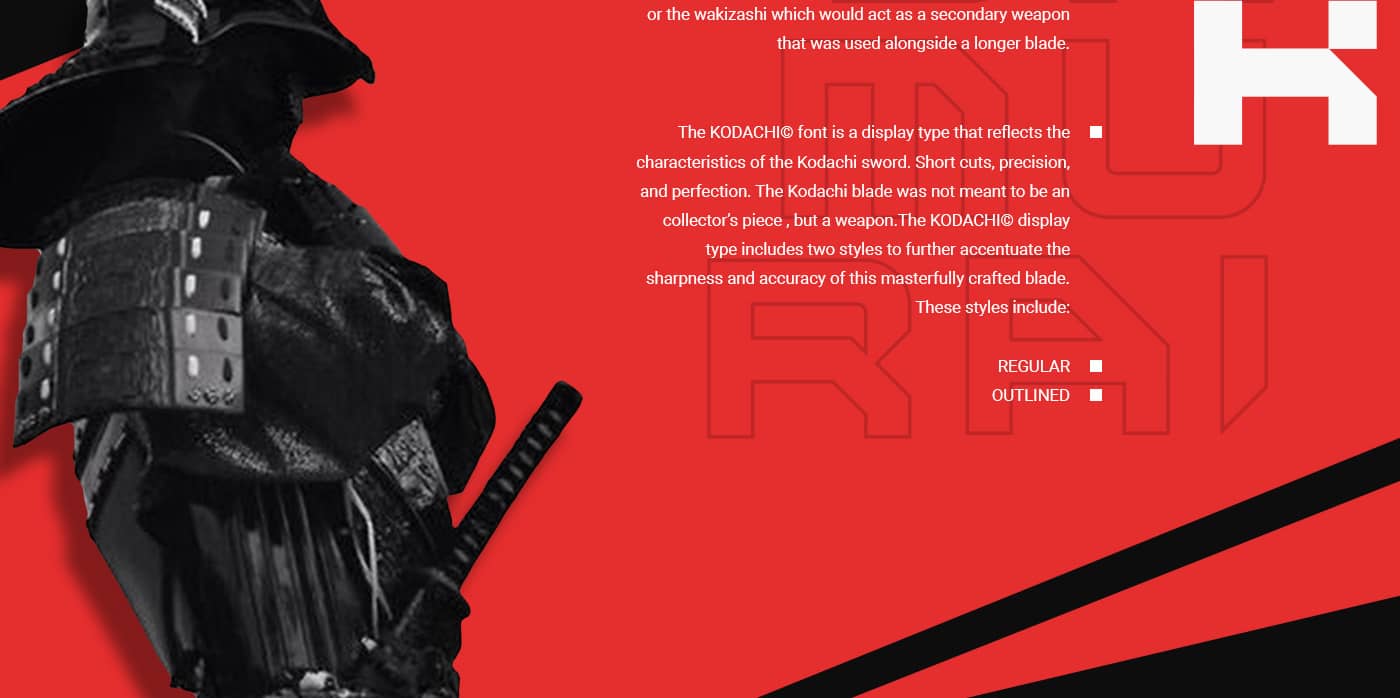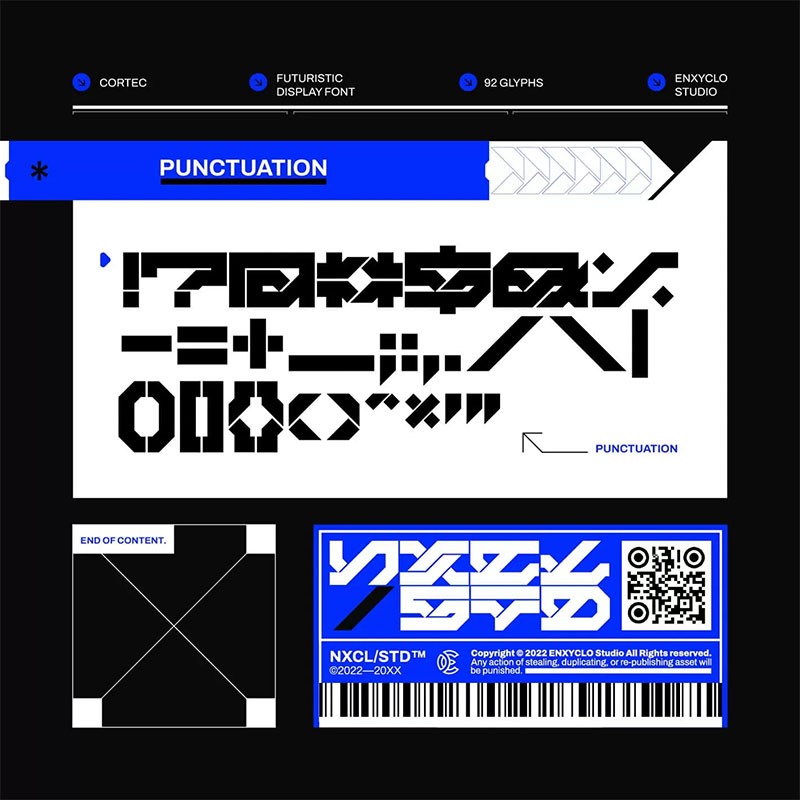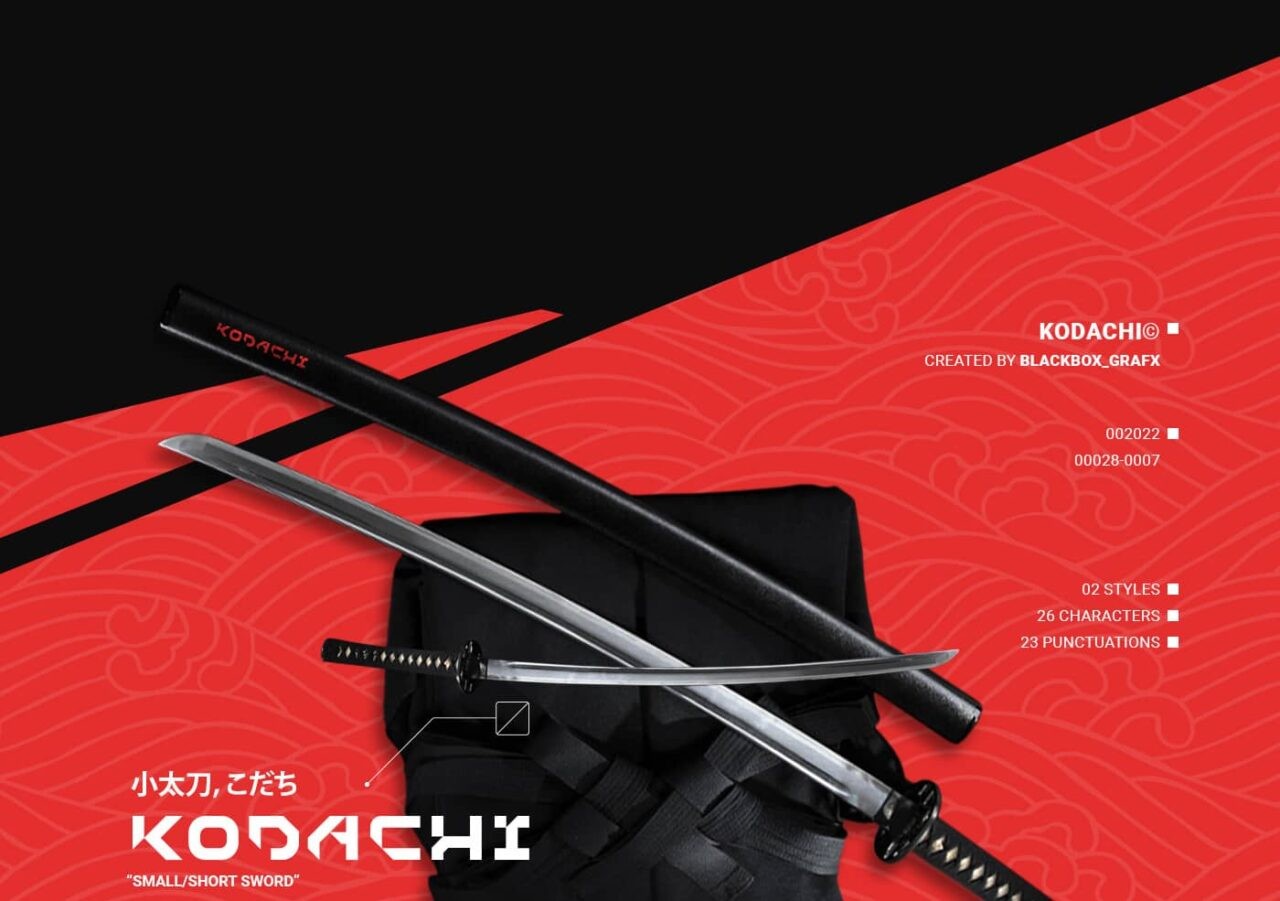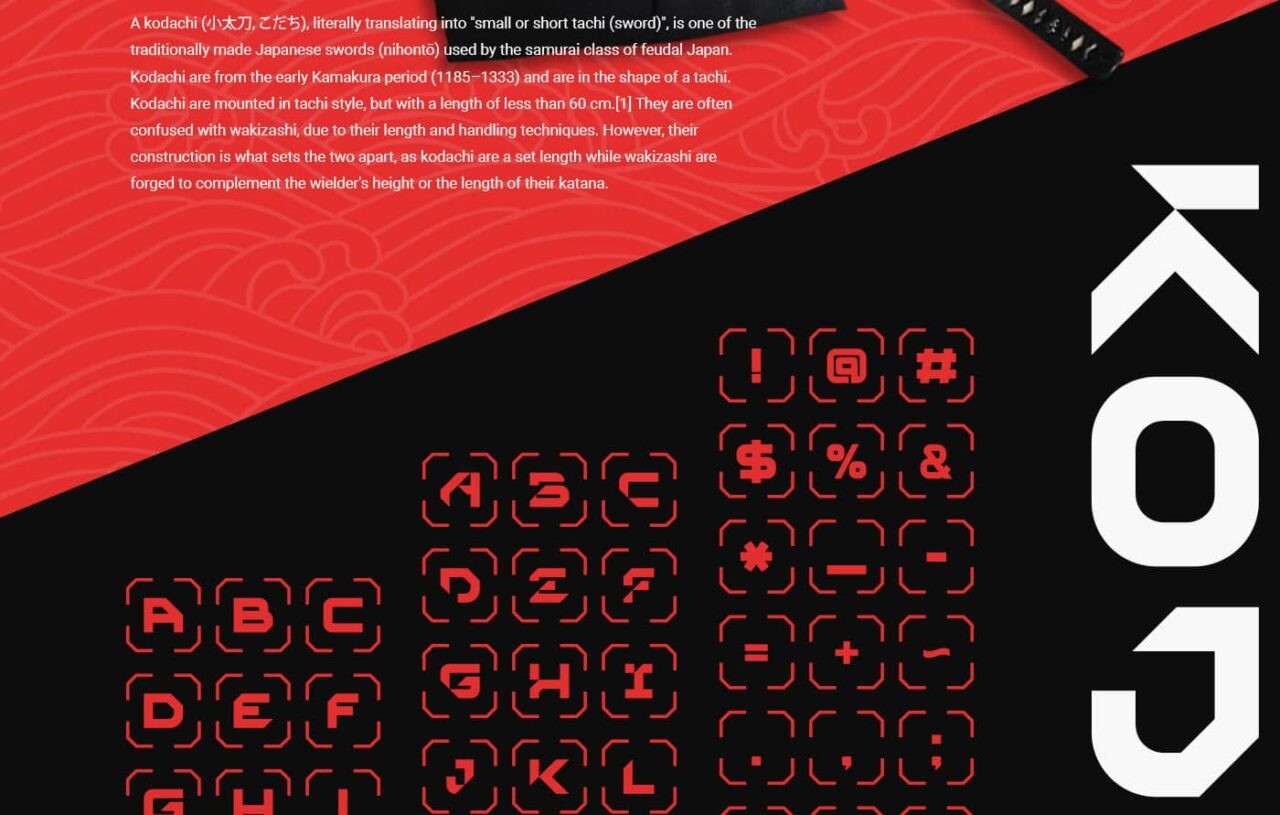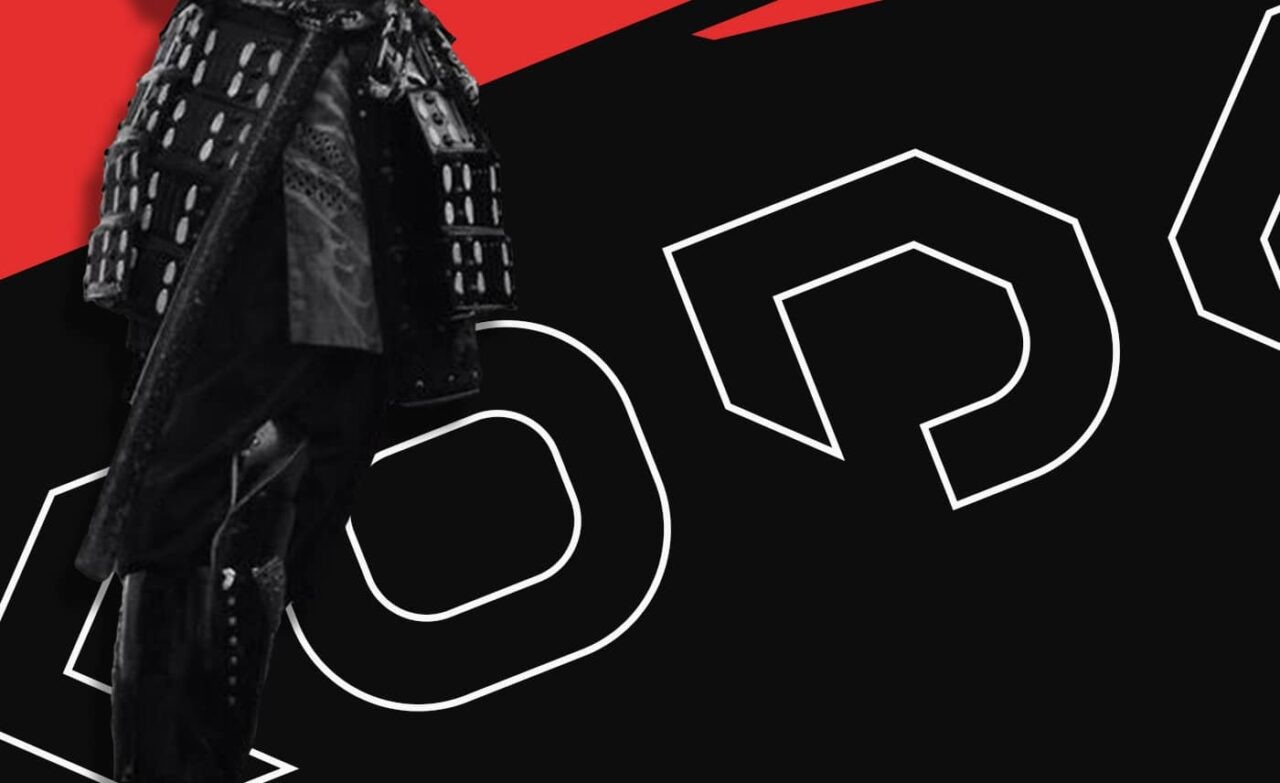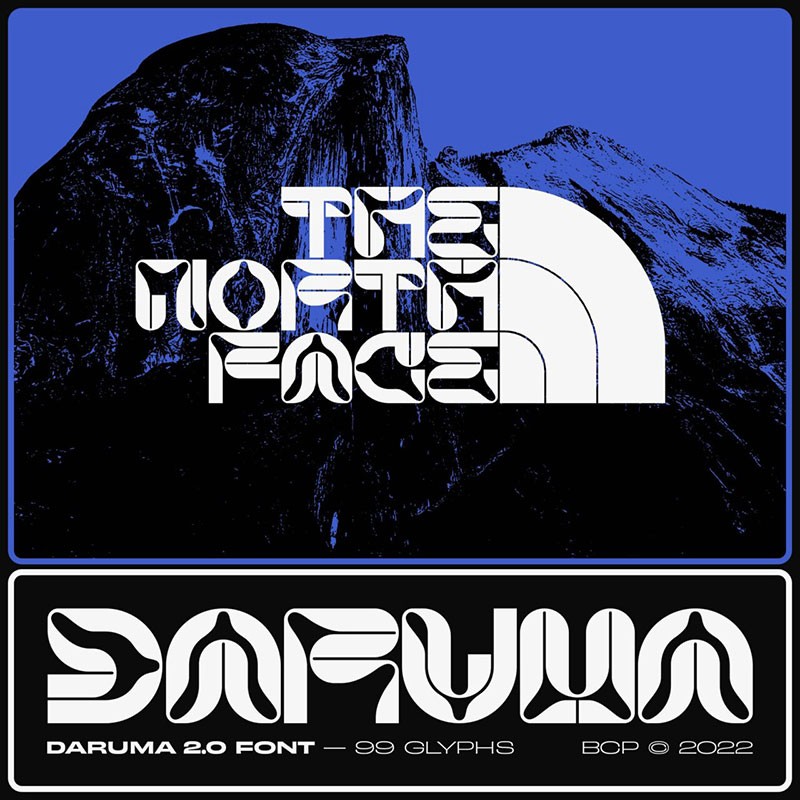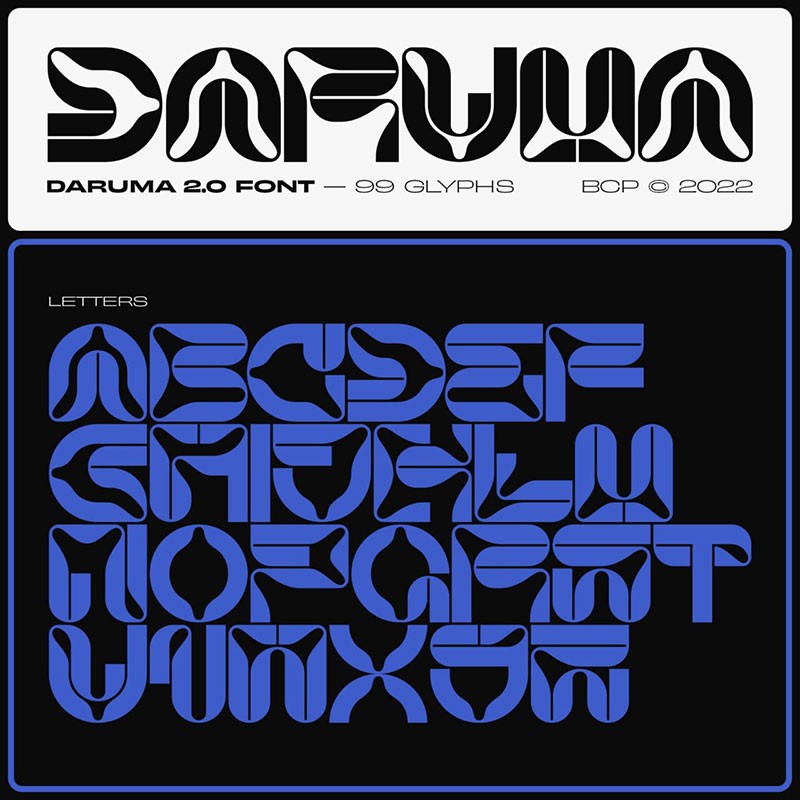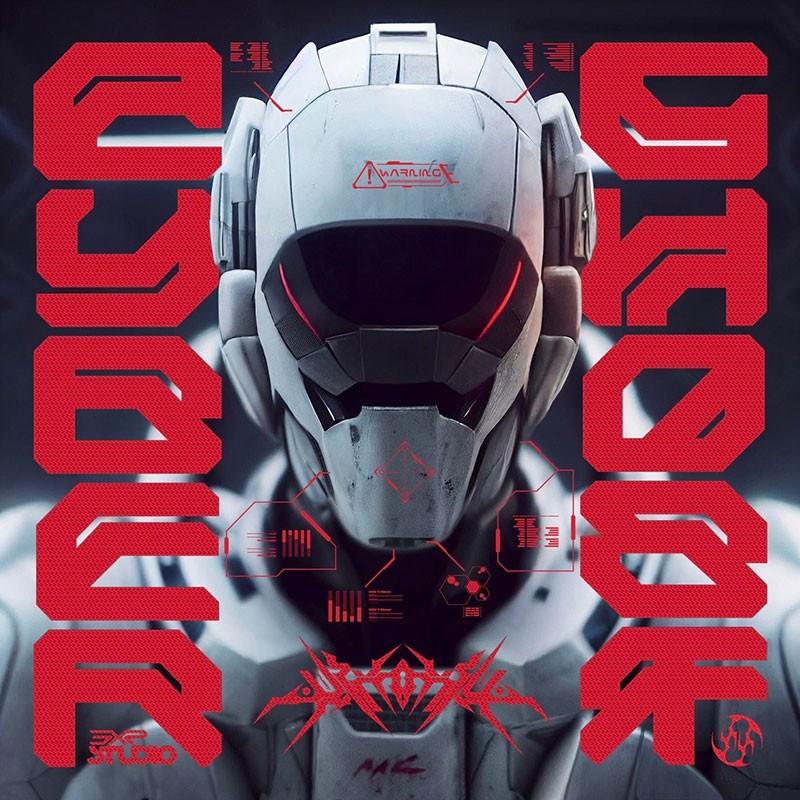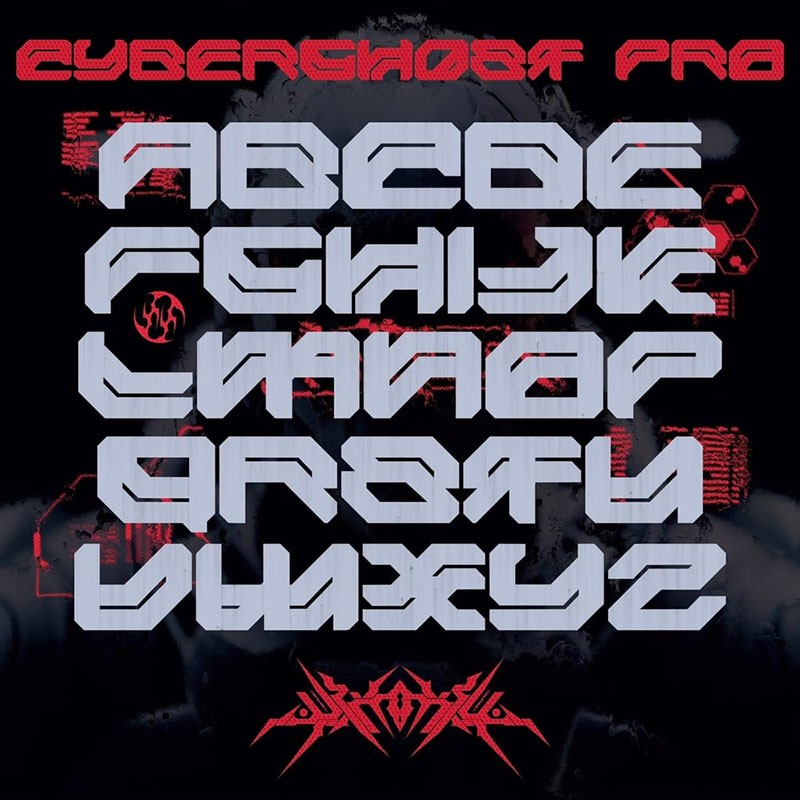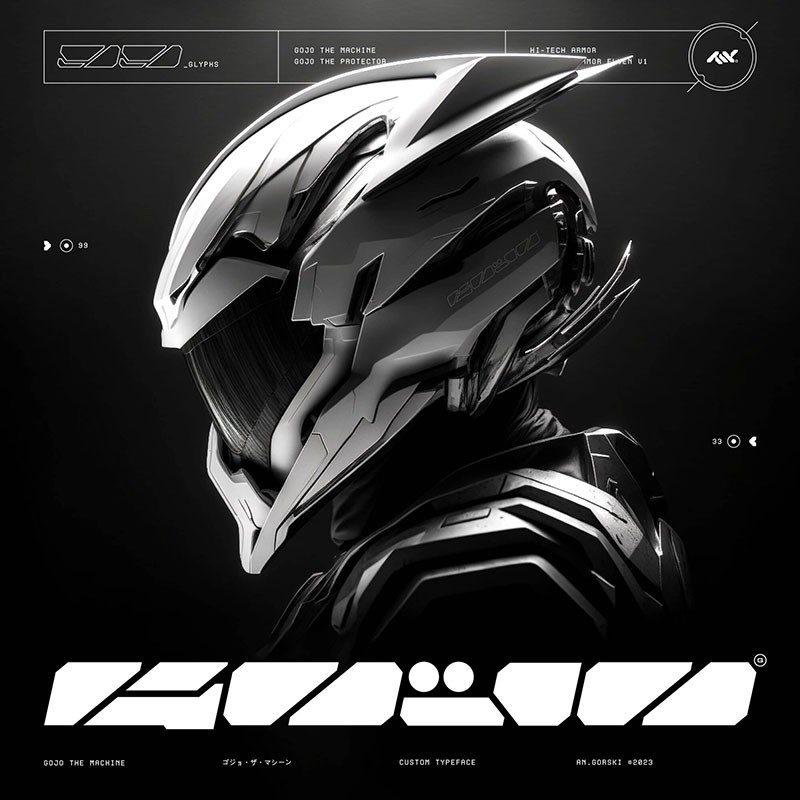
22款未来感科幻机甲风格的英文字体合集
在这个合集中,汇集了一系列展现未来感科幻机甲风格的英文字体,让你的设计作品更具创新与独特性。每款字体都带有强烈的科技氛围和机械力量。无论你是在设计海报、插图、游戏界面还是其他创意项目,这些字体都能为你的作品带来令人惊叹的未来感。
CORTEC
这款字体的设计灵感来源于机械装置和科技元素,给人一种未来世界的感觉。它适用于各种设计项目,例如海报、标志、网页设计等,能够为作品增添独特的现代风格和创新感。
Kodachi
一款日式机甲风字体,具有简洁而精细的字形,强调了几何形状和直线线条。它的设计灵感来自于科技、数码和未来元素,呈现出一种现代科技的感觉。字母间的间距均匀,字体线条流畅,给人一种清晰、现代而富有力量感的印象。
Aero Flux
一款极具机甲风的现代英文字体,设计灵感源自现代航空技术和飞行器的动态外观。其流畅的曲线和精细的线条营造出强烈的动感和科技感。Aero Flux共有8种字重,包括超轻、细、黑体和粗体,以及斜体和粗斜体等多样化的风格,适用于品牌标志、海报、网站设计、广告和印刷品等。
Daruma 2.0
CYBERGH0ST-PRO
一款具有赛博朋克风格和未来感的字体,呈现出科技、机械和数字元素的融合,为设计作品带来一种充满创新和前卫感的视觉效果。
Gojo
字体的字形由方块构成,线条粗犷而有力,呈现出一种坚固、稳定和重型的感觉。它的设计灵感来自于赛博朋克文化和科技未来的想象,展现出一种冷酷、机械化和前卫感的氛围。
Space X Noid
字形设计简洁、流畅且线条精细。它融合了几何形状和科技元素,呈现出一种现代化和未来感的视觉效果。字母之间的间距均匀,排版整齐,展现出专业性和科技感。
Briske
一款抽象的科技未来字体,字形设计充满了抽象的几何形状和线条,以其独特的外观和前卫感而脱颖而出。它展现出一种现代化和科技感的视觉效果,适合用于各种与科技、创新和未来相关的设计项目。
Plaztma(可商用)
字形设计充满了锐利的边缘和几何形状,呈现出一种坚固、稳定和机械化的感觉。它的笔画粗犷有力,字母间的间距紧凑,使得排版显得紧凑而有力量感。这种设计风格突出了机甲风格的特点,给人一种强烈的科技感和机械力量的视觉冲击。
Hermione(可商用)
一款突出现代感和未来感的字体,以其独特的外观和科技氛围而著称。它是一种无衬线字体,适用于各种科技、创新和未来主题的设计项目。
Damages Pro
一款独特的视觉风格。字母的形状不完全符合传统的字母形态,而是通过创意和抽象的方式表达字母的形象。这使得它在视觉上更具有吸引力和独特性。
Phaser
字母的形状流畅且线条精细,呈现出一种前卫、激进和充满活力的视觉效果。它融合了赛博朋克的元素,将其原始能量和狡黠的美学融入字体设计之中。
Blackbox
这款英文字体的设计灵感源自于科幻机甲和赛博朋克风格,线条流畅、锐利,充满现代感和未来感。字体包含常规和轮廓两种风格,可满足不同需求的使用,适合用于强调品牌的现代感和科技感。
Revanox
一种充满现代感、科技感和未来感的字体。字母的线条流畅,角度锐利,呈现出一种现代化和科技化的视觉效果。
Neckle
字体的字形设计突出了机械化和科技化的特征。字母的线条精细且角度锐利,呈现出一种坚固、稳定和先进的视觉效果。它融合了人工智能和机甲风格的元素,展现出一种强大而独特的氛围。
Sentinal
一款充满机械风格的字体,融合了现代科技和机械力量的特点,特别适合用于与机械、科技、工业相关的作品。
SKY8AS3-NEUTRAL
一款充满机甲风格的字体,融合了未来感和坚固力量的特点,特别适合用于与机甲、科技、未来世界相关的作品。
Chipunk
一款粗体的机甲风格字体,字母的线条粗壮、角度锐利,呈现出一种强大、稳定和粗犷的视觉效果,特别适合用于与机甲、科技、未来世界相关的作品。
EXOBYTE
一款机甲风格的字体,其字形呈现直角曲折的特点,突显了机械化和科技感。
Drones
一款机甲风格字体,字母之间的线条相互交错,形成了一种错综复杂的外观,它融合了交错形和机甲元素,给人一种充满未来感的视觉效果。
BI0Z0N3
一款专为机甲主题而设计的英文字体,它通过细节的处理和特定的设计元素,展现出强烈的机械、科技和动态的特点。它适用于各种机甲相关的设计项目,如游戏、电影、插图等,为作品增添独特的视觉效果。
Achron(可商用)
一款可商用的机甲元素英文字体,它融合了机械、科技和未来主义的风格,为设计师和品牌提供了丰富的创意选择。